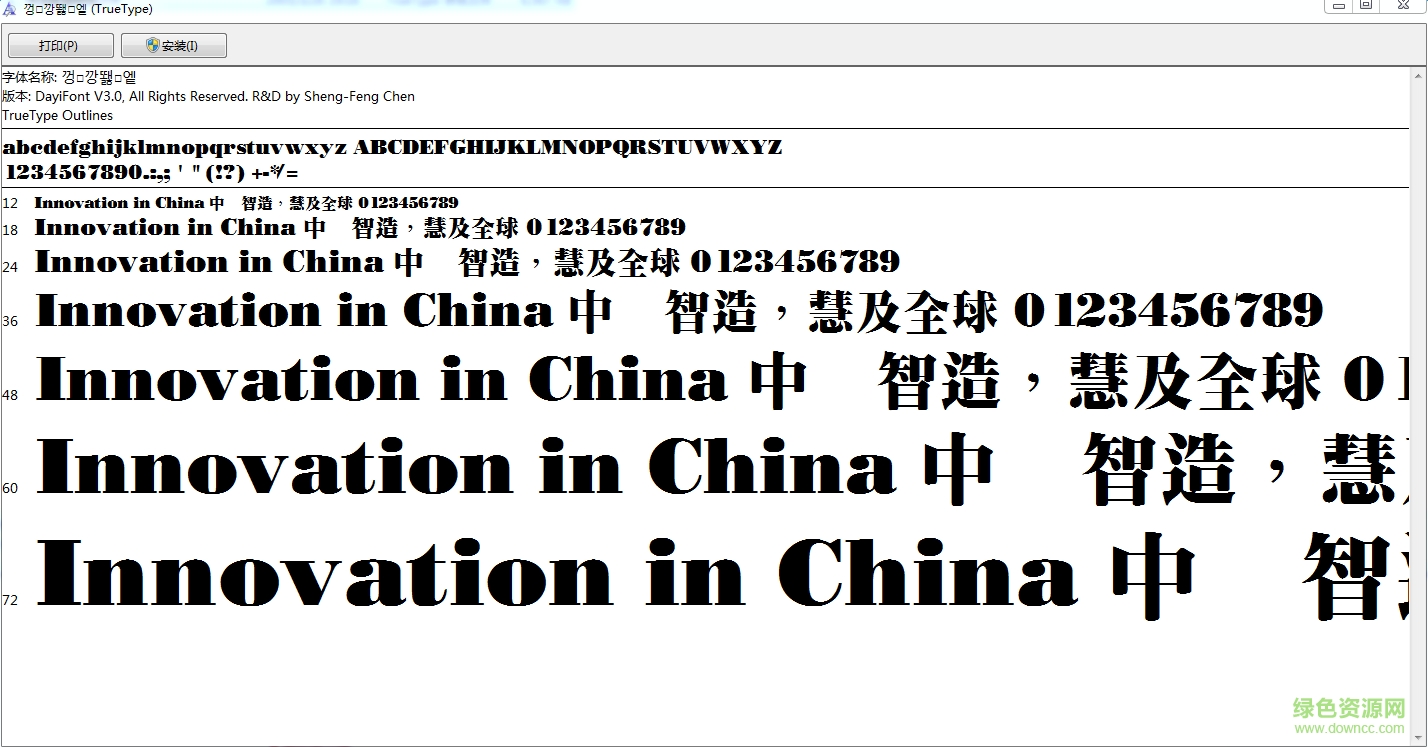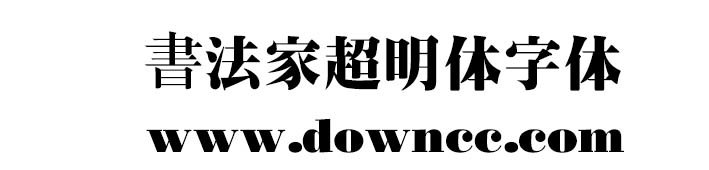
書法家超明體字體
書法家超明體繁體是一款非常精美的字體,筆畫鏗鏘有力,結(jié)構(gòu)對稱,適用于各種廣告印刷,小編已為大家打包好了,下載解壓即可使用,有需要者歡迎在綠色資源網(wǎng)下載!
書法家超明體繁體介紹
書法家超明體繁體是一款宋體字體,是根據(jù)古代的印刷字體打造而來,筆畫的豎向線條較粗,橫向較細(xì),平時(shí)的書刊報(bào)紙使用的都是宋體字體!